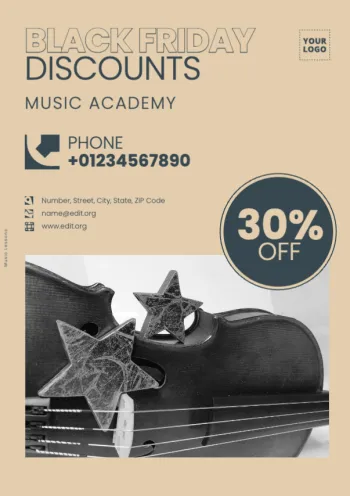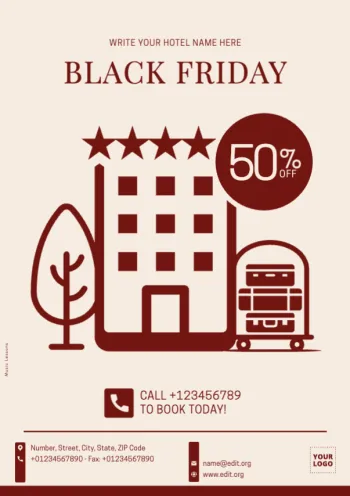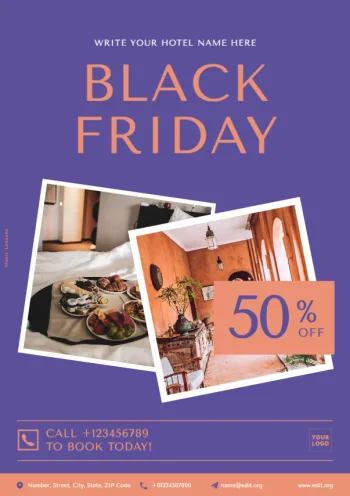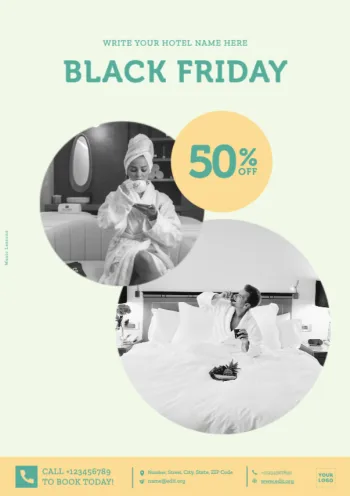
Im Online-Editor von Edit.org findest du Hunderte von kombinierten Schriftarten, mit denen du deine Vorlagen noch spektakulärer und origineller gestalten kannst.
Die besten Typografie-Kombinationen für deine Designs
Die Typografie ist genauso wichtig wie das Bild, da sie oft die Grundlage für das Gesamtdesign eines Artikels bildet. Der Buchstabe kann uns über viele Dinge informieren und tatsächlich verwenden Marken Typografien je nach den Werten, die sie ihrem Publikum vermitteln wollen (eine elegante Bekleidungsmarke wird zum Beispiel niemals Typografien verwenden, die urban oder modern sind). Aus all diesen Gründen solltest du eine Schriftart vorher studieren und es vermeiden, nach dem Prinzip von Versuch und Irrtum vorzugehen.
Es gibt Millionen verschiedener Schriftarten, und bisher haben wir bei Edit.org eine Auswahl derjenigen getroffen, die unserer Meinung nach am besten für deine Entwürfe geeignet sind: klar, auffällig und nach deinem Geschmack veränderbar.
Vor kurzem wollten wir noch einen Schritt weiter gehen. Genauso wie du Vorlagen auswählen kannst, kannst du jetzt auch Schriftkombinationen auswählen.
So fügst du typografische Schriftkombinationen in deine Designs ein
Frei bearbeitbare Vorlagen mit Typografie-Farbkombinationen
So einfach ist das! Das Endergebnis deiner Kreation wird so aussehen, als hätte sich ein Grafikdesigner darum gekümmert, genau wie du es dir vorgestellt hast. Du sparst Zeit und Geld, wenn du es selbst und von jedem Gerät mit Internetanschluss aus machst.
Wenn du eine Vorlage für dein Unternehmen bearbeitest, denke daran, dass du dich wie immer an der Unternehmenslinie der Marke orientieren solltest: gleiche Farben, Schriftart und Logo. Auf diese Weise vermittelst du ein solideres und einheitlicheres Bild deines Projekts.